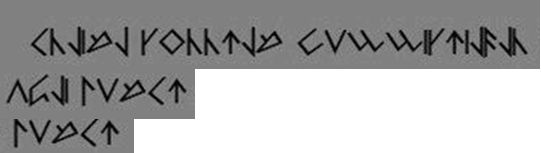
unbekannte Symbole / Zeichen - Identifizierung
hab mich schon ne weile hier bei euch im Forum durchgelesen, allerdings bin ich nicht so richtig fündig geworden. Vielleicht kann mir jemand von euch helfen, bin auf der Suche nach den Symbolen
Habe hier im Forum vorgeschlagene Online Entschlüsselungen bereits genutzt, leider auch ohne Erfolg.
Die Symbole sehen nach Futhark Runen aus, ein paar sind identisch aber die anderen sind es nicht.
das sieht mir eher nach einer Kinder-Geheimschrift / Runen-Alphabet in diesem Stil aus:
Na gut, wenn es dann noch kein Bild gibt, muss ich wohl auch mal meine Kristallkugel bemühen, auch wenn die nicht ganz so exakt arbeitet, wie Bertels...
Könne es dies hier sein:
dann handelt es sich um Cirth, Tolkiens interpretation der Runen aus „Der Herr der Ringe“
Die Cirth ‚Kerbzeichen‘ ähneln äußerlich noch immer den germanischen Runen, aber nur noch wenige entsprechen ihnen tatsächlich noch. So wie bei den germanischen Schriftzeichen hat sich also auch die Schrift in Mittelerde weiterentwickelt. Hierbei hat sich Tolkien eng an die wissenschaftlichen Fakten in der Geschichte der germanischen Runenschrift angelehnt.
Für mich sieht das auch eher nach einer Phantasieschrift aus, mir fiel spontan "Marsianisch" ein ...
Leider liegt Ihr daneben, bei euren Vorschlägen fehlen noch einige Symbole,
so das es mir noch nicht weiter hilft.
Leider liegt Ihr daneben, bei euren Vorschlägen fehlen noch einige Symbole, so das es mir noch nicht weiter hilft.
Hast du dir unsere Beiträge auch durchgelesen? Zwei von drei antworten dir "das wird eine Phantasieschrift sein".
Vielleicht versorgst du uns auch mit Informationen zu den gesuchten Zeichen – woher stammen diese, wo werden sie verwendet, gibt es noch mehr davon … dann steigt die Chance, dass dir geholfen werden kann.
Für mich sieht es wie ein Font aus, also nicht handgeschrieben, da die einzelnen Zeichen sehr gleich sind. Allerdings kenne ich aus keinem Runenalphabet Zeichen mit doppelten vertikalen Strichen, daher liegt nahe, dass es eine Kinder-/Geheim-/Phantasieschrift ist.
ist definitiv keine Phantasieschrift,
stammt aus dem Geschichtsunterricht meiner Tochter, Gynmasium 9.Klasse.
Bei denen läuft gerade ein Projekt über nordische Mythologie.
u.a. war eine Aufgabe die Schrift zu ermitteln,
wobei ich das auch zu hoch gegriffen finde das im Unterricht zu bringen.
Da würde mich die Auflösung brennend interessieren, hoffentlich löst die Geschichtslehrerin das auf. Ich habe bei keiner Rundenschrift solche Doppelzeichen gefunden, daher stimmt irgendwas mit den Zeichen nicht oder die Lehrerin ist einem Geocacher aufgesessen ;-)
Dann sind diese Doppel-Senkrechten wohl einer sehr schlecht zugerichteten Runenschrift geschuldet und man mus hier mal kräftig dran nacharbeiten.
das sieht mir eher nach einer Kinder-Geheimschrift / Runen-Alphabet in diesem Stil aus:
Das entspricht nicht ganz den Runen des OP, sollte aber aus der gleichen Ecke kommen. Das ist sowas wie die „elder Futhark“. In meinen ungeübten und trüben Augen sind einige Zeichen seltsam, was aber nix bedeuten muss, denn es gab sehr viele Varianten der Runen. Die doppelten Striche beim OP sind möglicherweise Ligaturen? Hier mal einen Link in dem man die Bandbreite der Variationen der einzelnen Runen erahnen kann:
Das sind vermutlich bis wahrscheinlich irgendwelche Futhark-Runen aus dem nordeuropäischen Raum und der Zeit vor bis kurz nach der Christianisierung.
Wobei viele der heute bekannten Umsetzungen für Rollenspiele und Psychokacke reiner Dekokram sind. Da wäre noch hier ein Link für Runen plus Capitalis Monumentalis (für die Unerschrockenen der furchtlosesten Typophilister):
Bitte aber beachten, dass das eine reine Erfindung des Dichters Edward Williams ist und nichts mit walisischen Barden oder einer überlieferten Runenschrift zu tun hat.